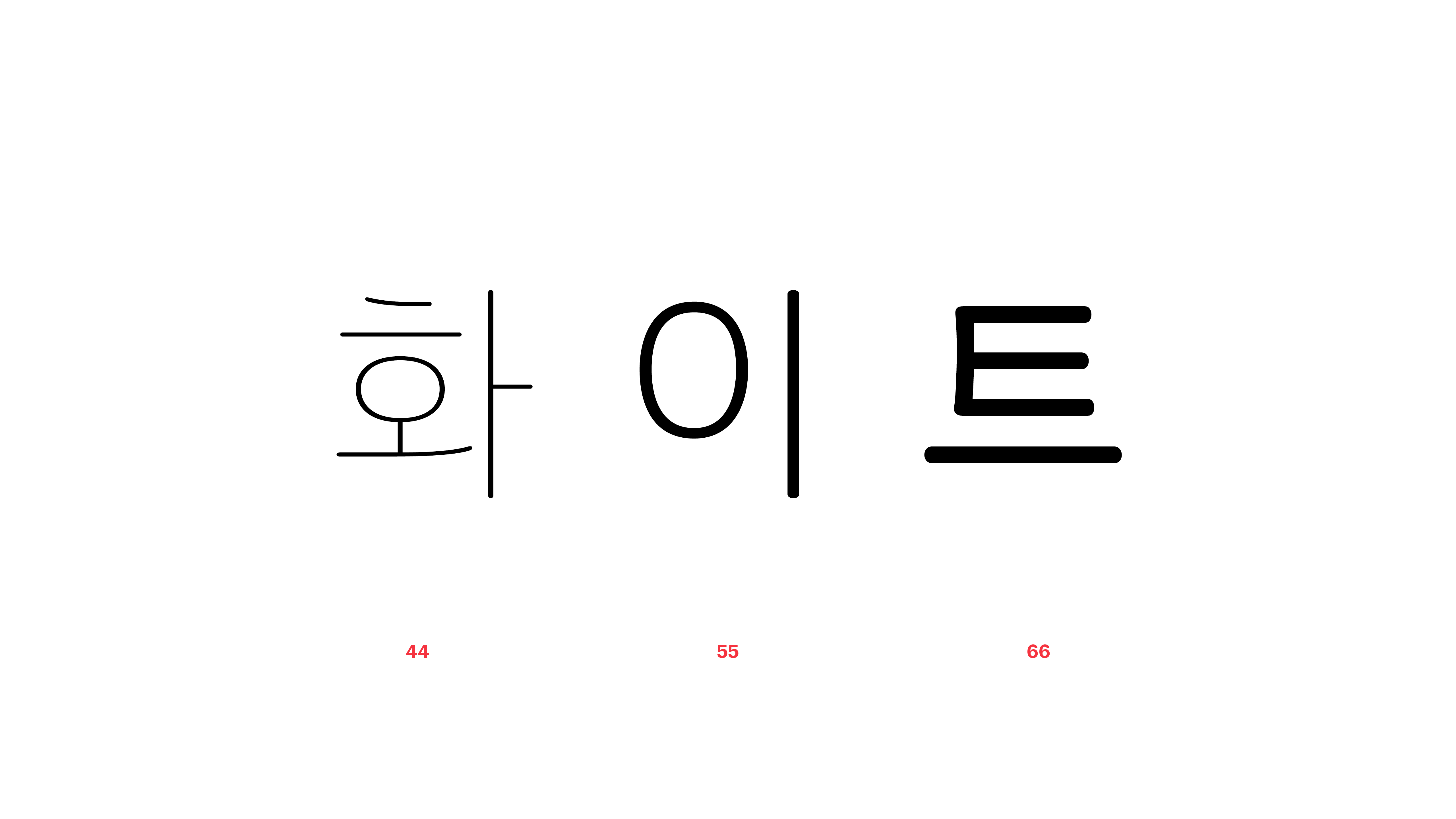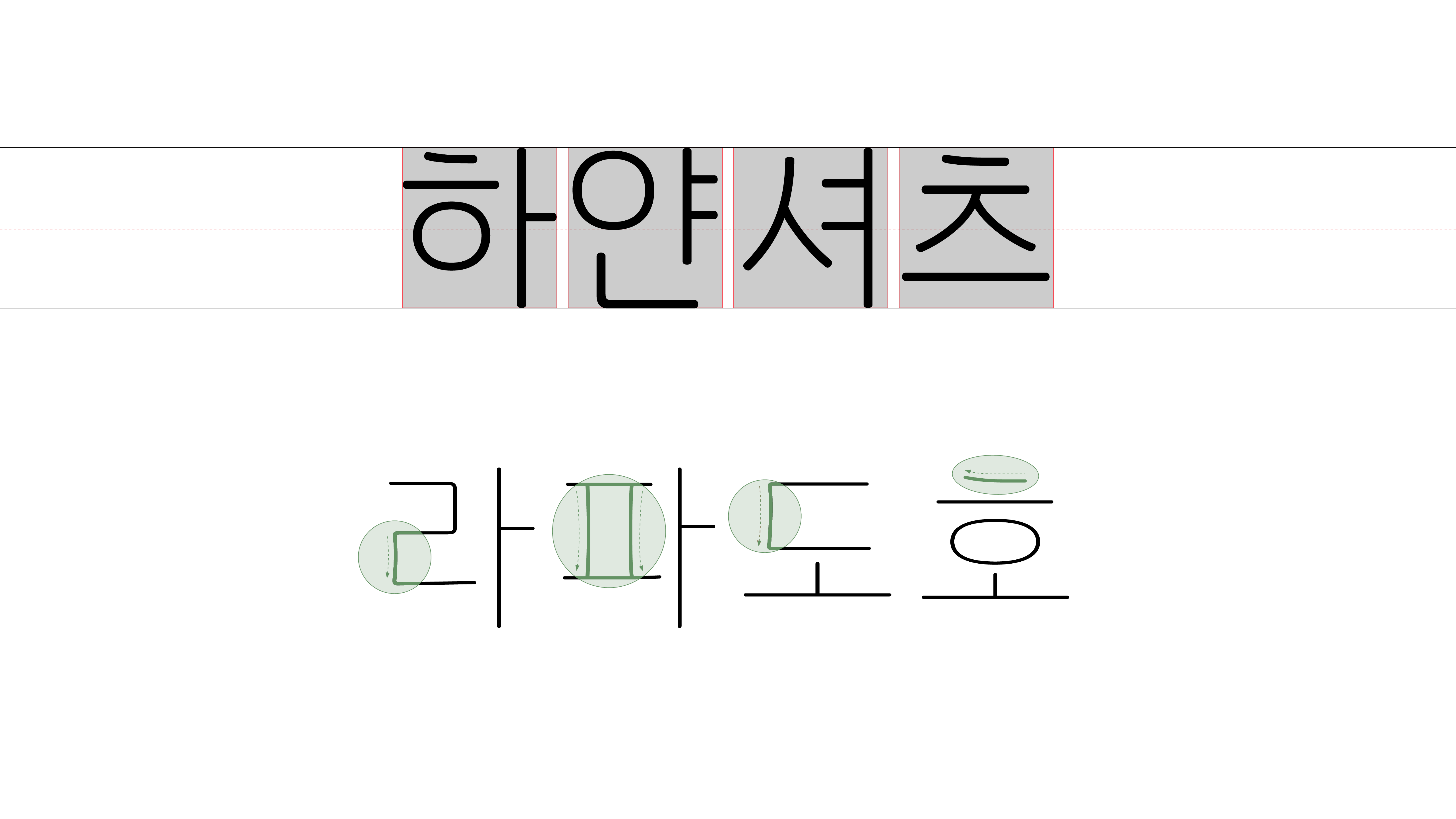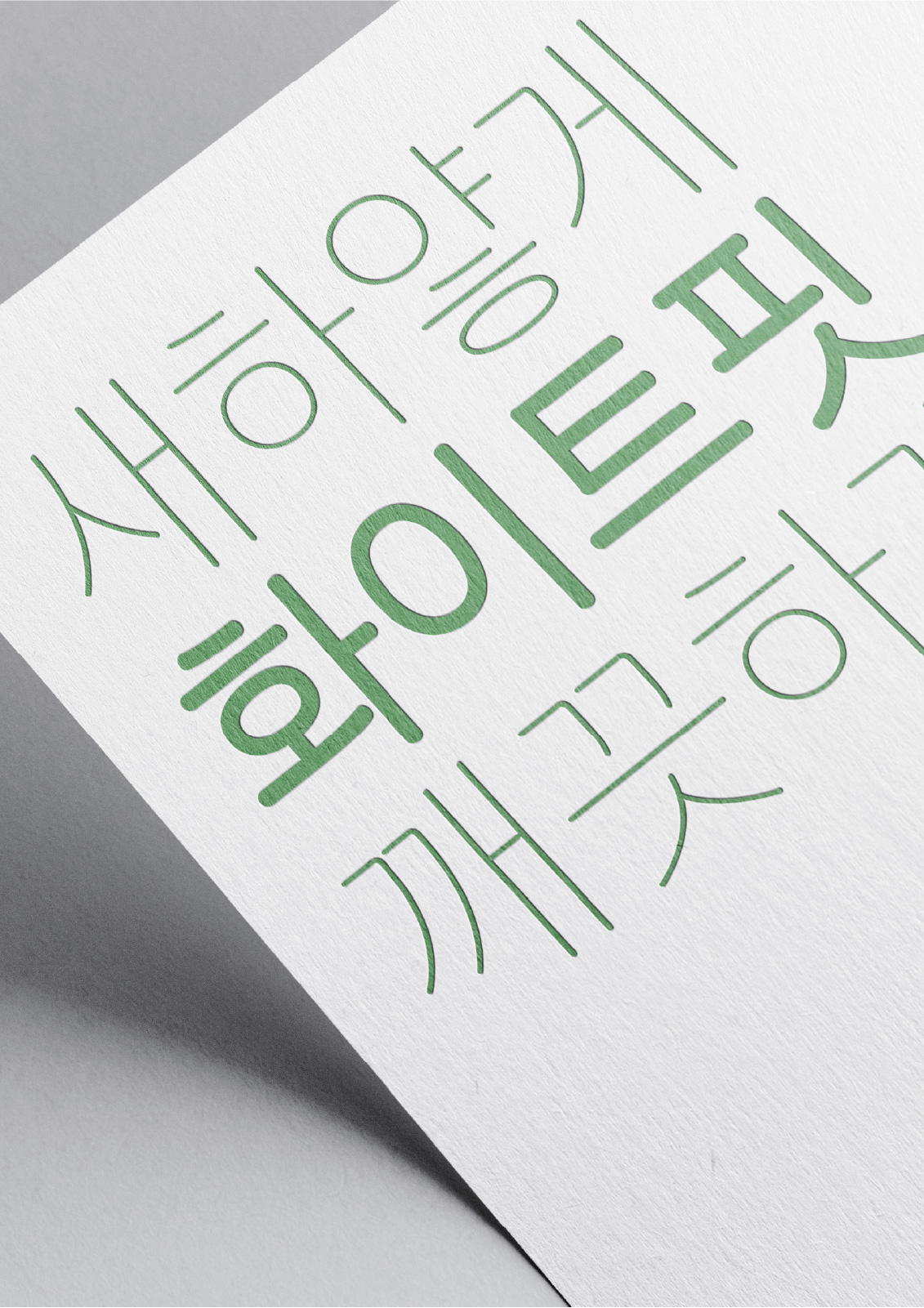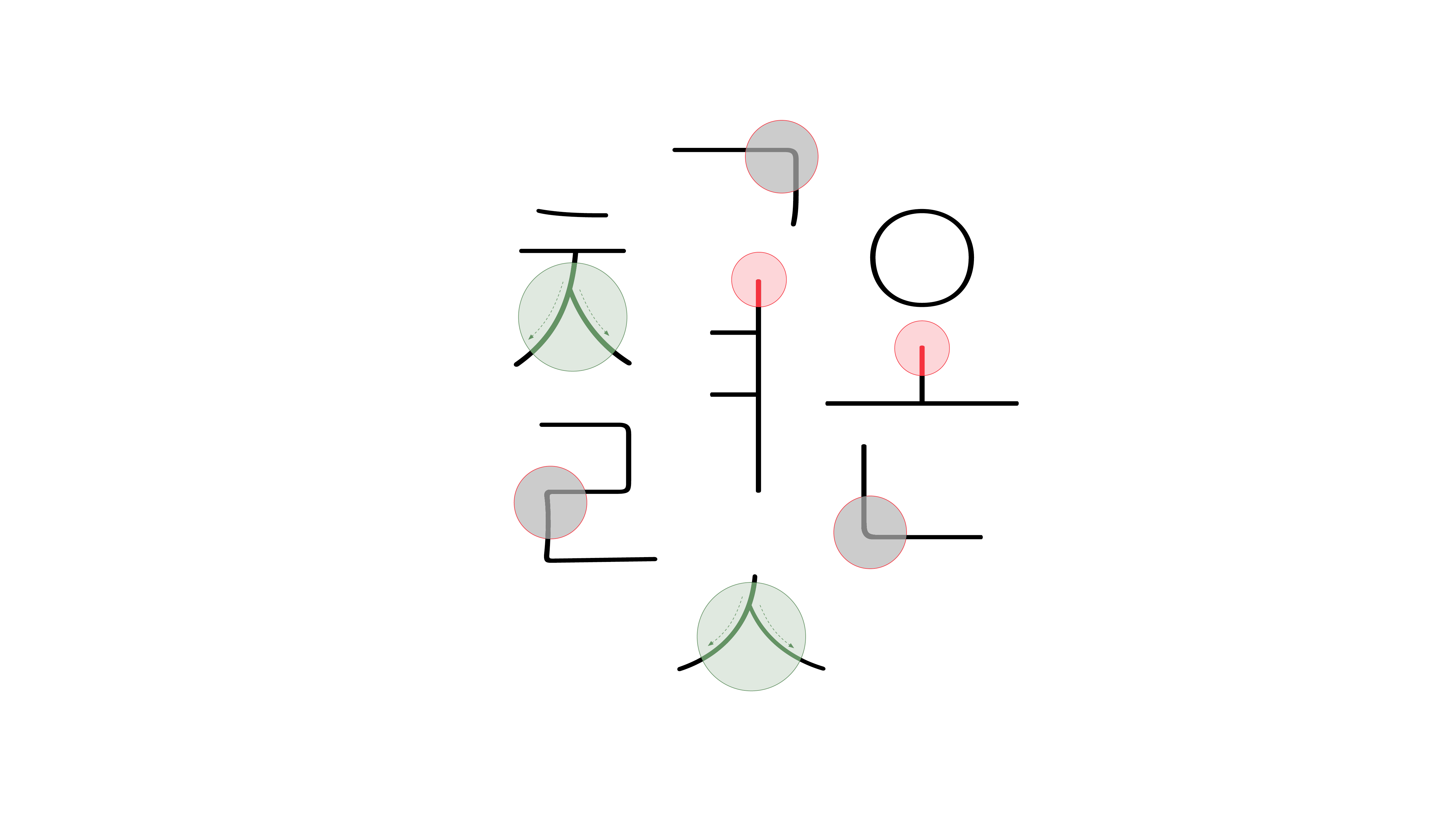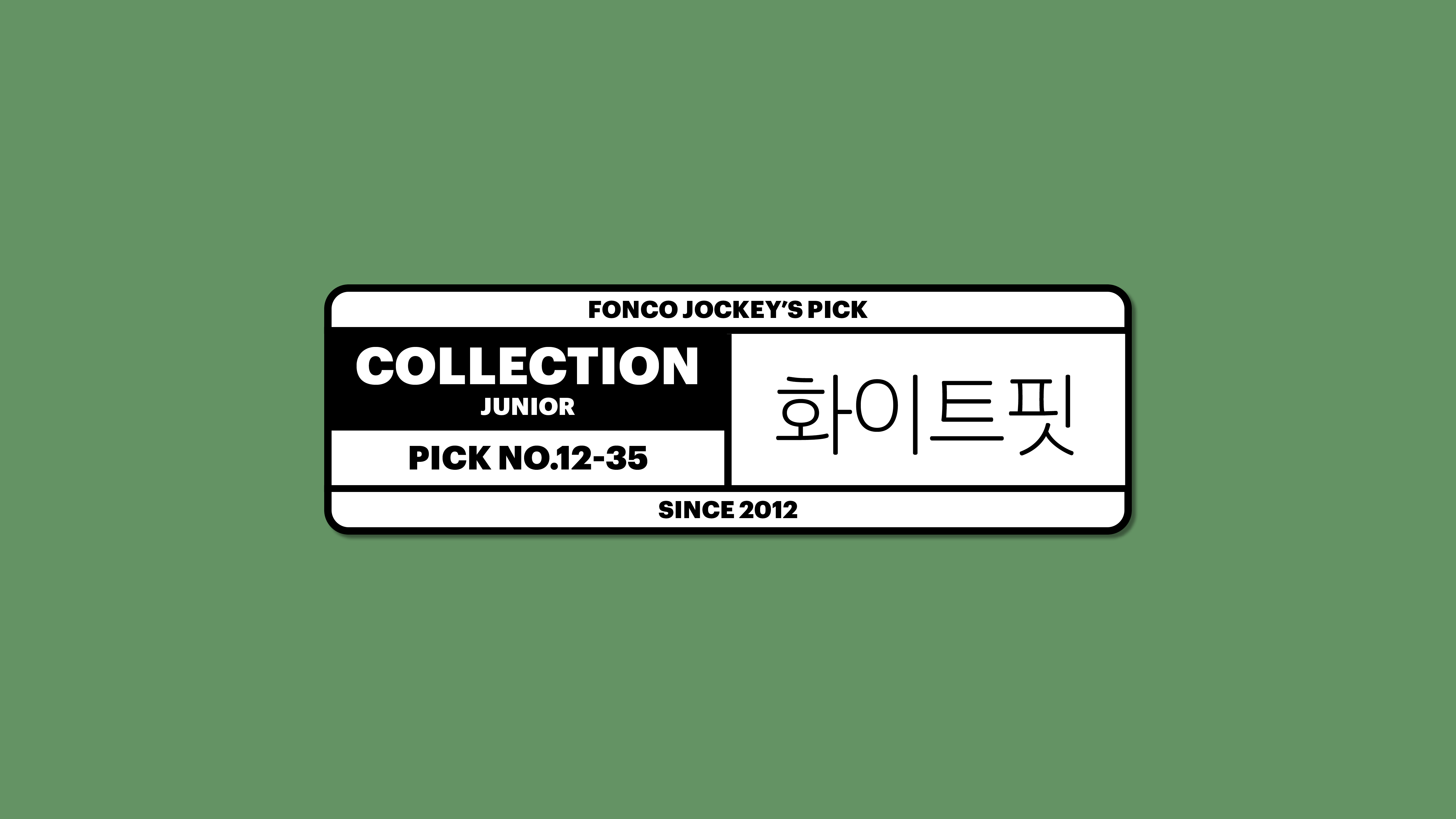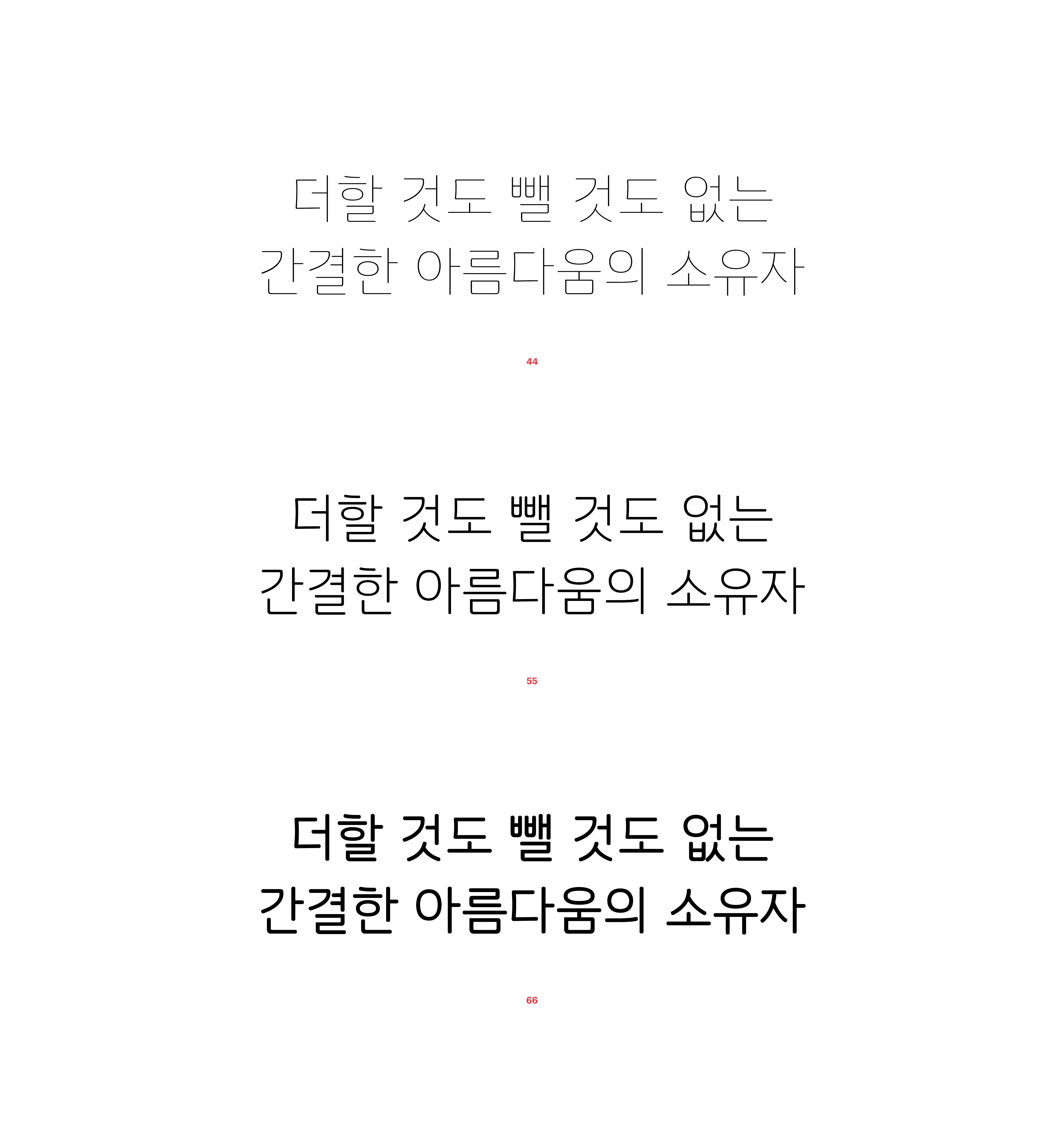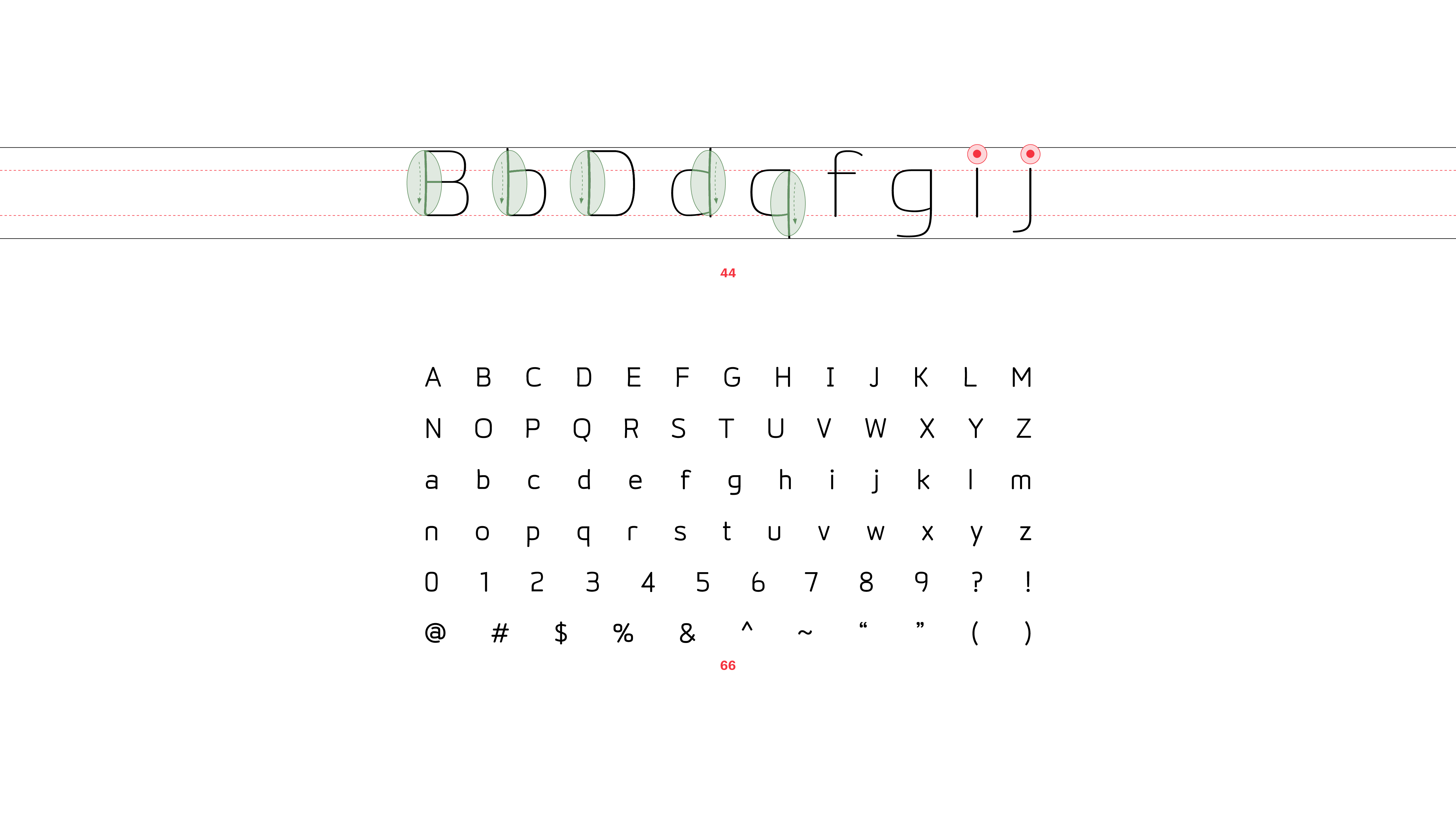
화이트핏
Yoon 화이트핏
보송보송 새하얀 셔츠를 잘 다려 입고 외출할 때, 더할 것도 뺄 것도 없는 산뜻한 느낌. 화이트핏체는 그 밝지만 세련된 느낌을 고스란히 재현한 폰트입니다. 예민한 획과 깔끔한 곡선이 유연하게 어우러질 수 있도록, 한 자 한 자 다림질하듯 제작해두었답니다.